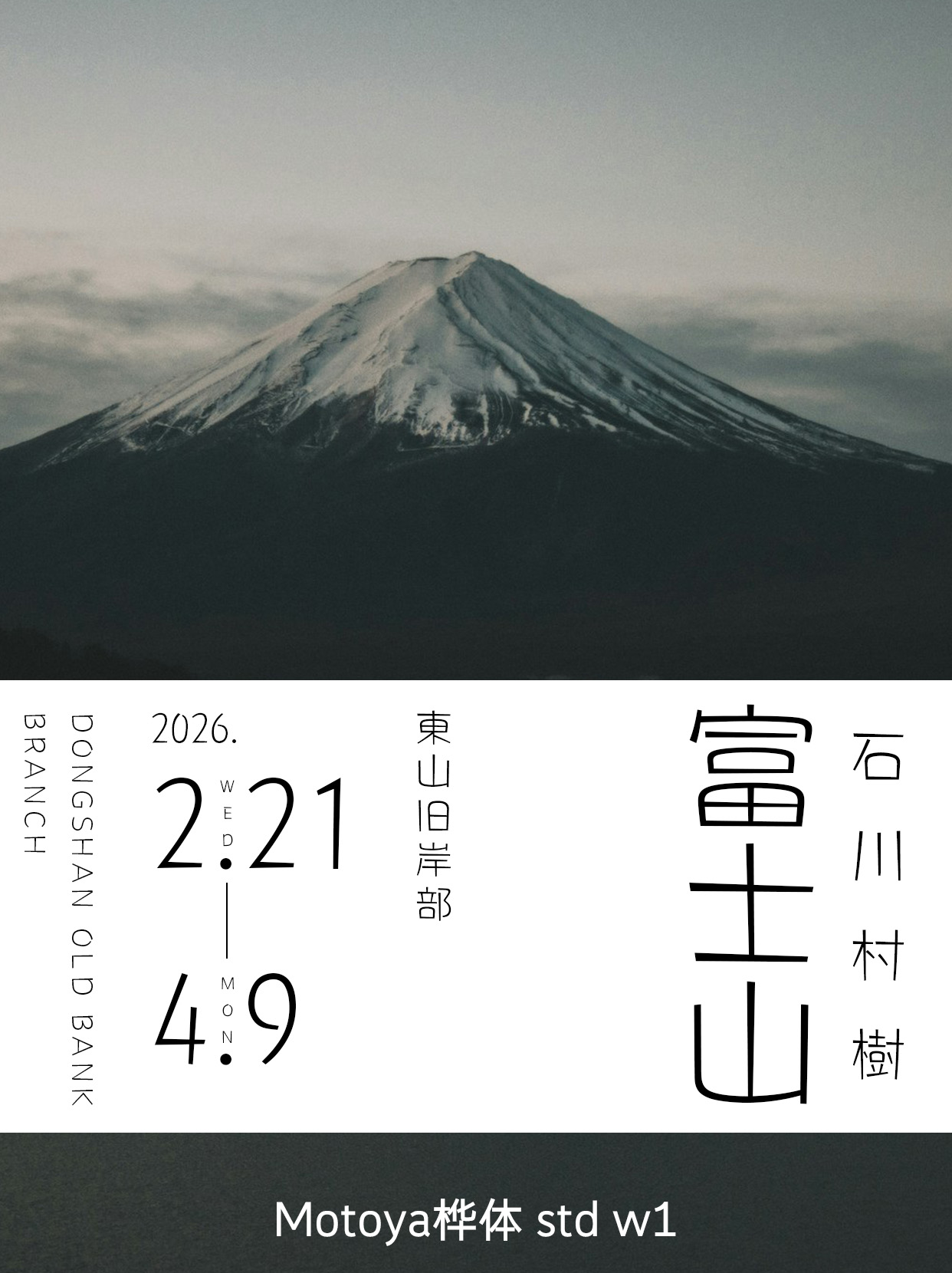
Motoya桦体 std w1
Motoya Birch Std W1
• 字体字重: 纤细(Thin)
motoya的Birch系列是兼具可爱和快乐的POP字体。Birch也就是“桦”是桦木科植物的总称,是继Cedar“杉”·Mulberry“桑”之后,同样以树木命名的。Birch的特征在于文字排版时呈现出的跃动感。使“口”等的字形上部呈圆形,通过缩小横线和竖线的笔画末端,表现出柔和以及锐利。可以广泛用于传单、海报、电视字幕等。每一个字都体现出POP字体的快乐,是让人非常有期待感的字体。